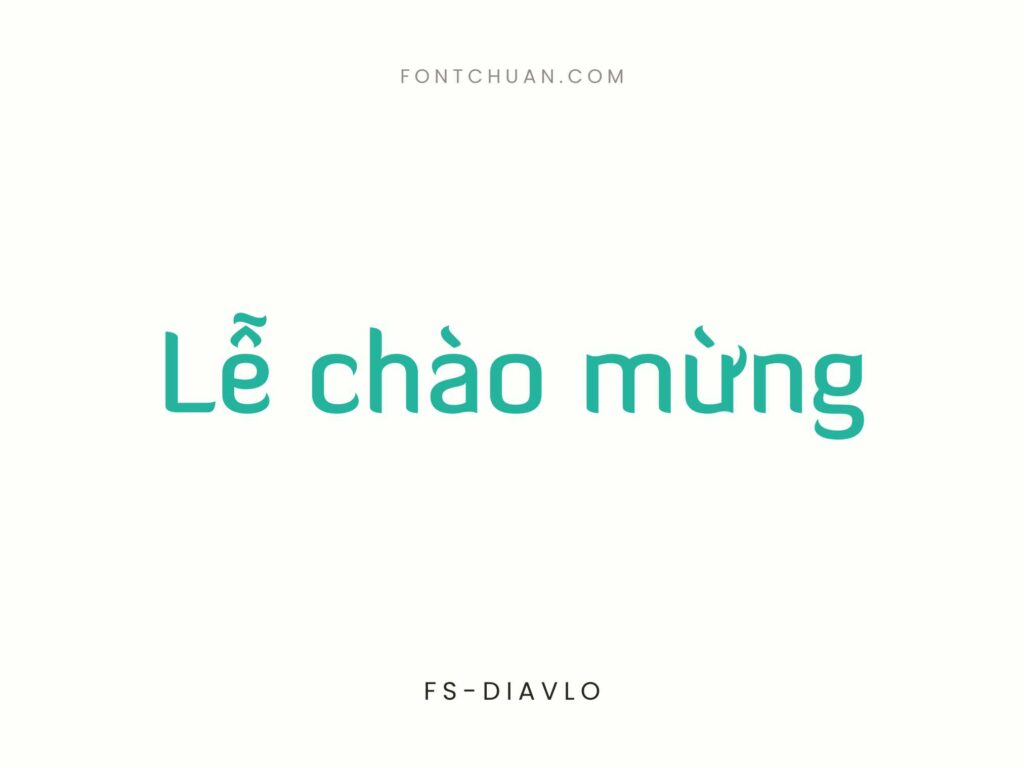
Font FS Diavlo Trọn Bộ Việt Hóa
Tác giả Font: Jos Buivenga
Diavlo là một họ font chữ sans-serif hiện đại, được thiết kế bởi Jos Buivenga và phát hành bởi exljbris Font Foundry vào năm 2007. Với 5 trọng lượng khác nhau: Light, Book, Medium, Bold và Black, Diavlo mang đến sự linh hoạt và đa dạng cho các dự án thiết kế. Font này nổi bật với các đường nét sắc sảo, góc cạnh và phong cách hiện đại, tạo nên sự mạnh mẽ và cá tính cho văn bản. Nhờ sự Việt hóa của Phông Chữ Việt, Diavlo hỗ trợ đầy đủ các ký tự tiếng Việt, giúp người dùng dễ dàng áp dụng trong các thiết kế đa ngôn ngữ. Thành viên của Font Chuẩn đã sưu tầm và chia sẻ font này nhằm đáp ứng nhu cầu của cộng đồng thiết kế.
Về đặc điểm thiết kế, Diavlo sở hữu cấu trúc hình học rõ ràng, độ tương phản thấp và các góc bo tròn tinh tế, mang lại cảm giác chuyên nghiệp và dễ đọc. Font bao gồm đầy đủ chữ hoa, chữ thường, số và các ký tự đặc biệt, cùng với hỗ trợ đa ngôn ngữ. Diavlo đặc biệt phù hợp cho các ứng dụng như thiết kế logo, tiêu đề, poster, bao bì sản phẩm và các ấn phẩm quảng cáo, mang lại sự nổi bật và ấn tượng cho thiết kế. Ngoài ra, font này cũng thích hợp cho các sự kiện như lễ hội, sinh nhật, Valentine và Trung thu, tạo không khí ấm áp và gần gũi. Trong lĩnh vực ngành nghề, Diavlo được ứng dụng rộng rãi trong quảng cáo, thiết kế thiệp cưới, giáo dục và công nghệ, góp phần tạo nên sự độc đáo và thu hút cho các sản phẩm và thương hiệu.